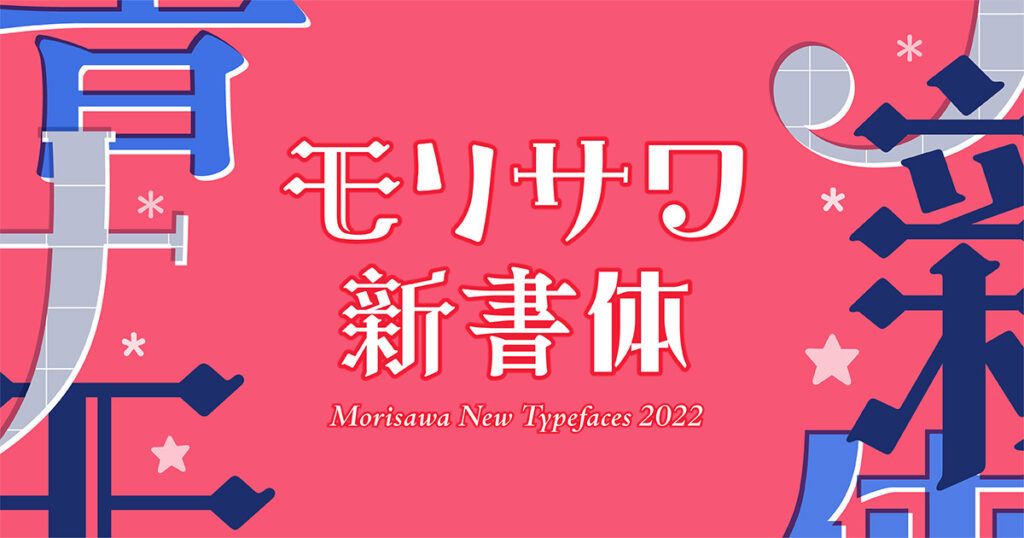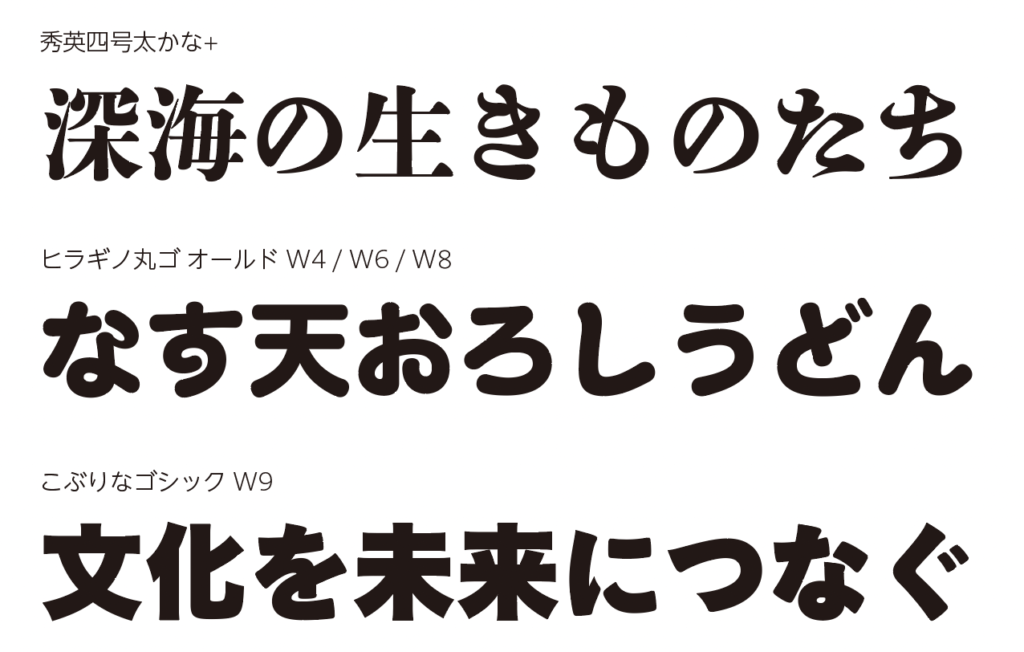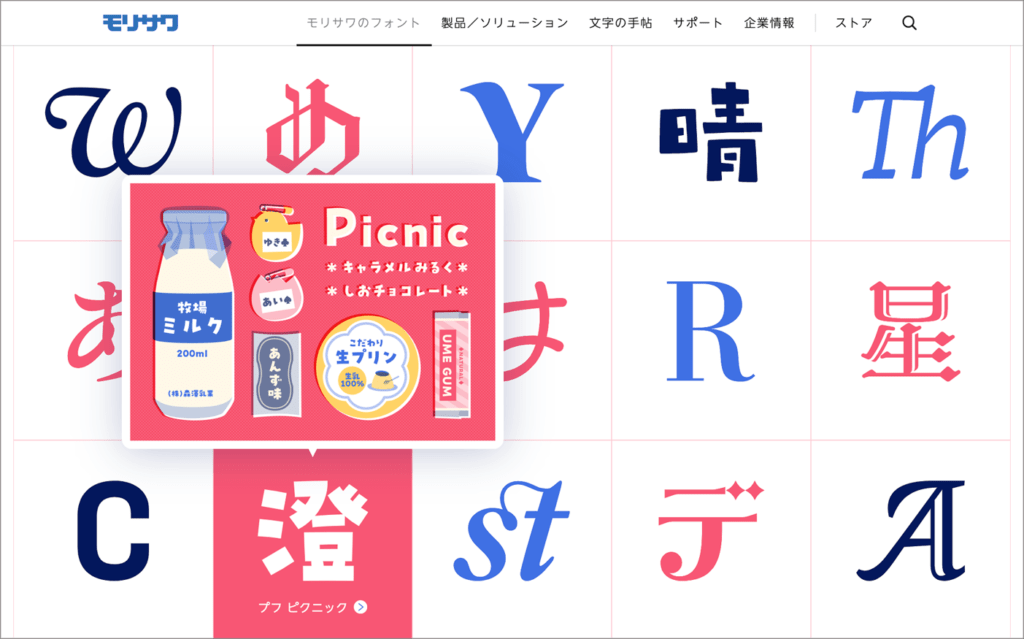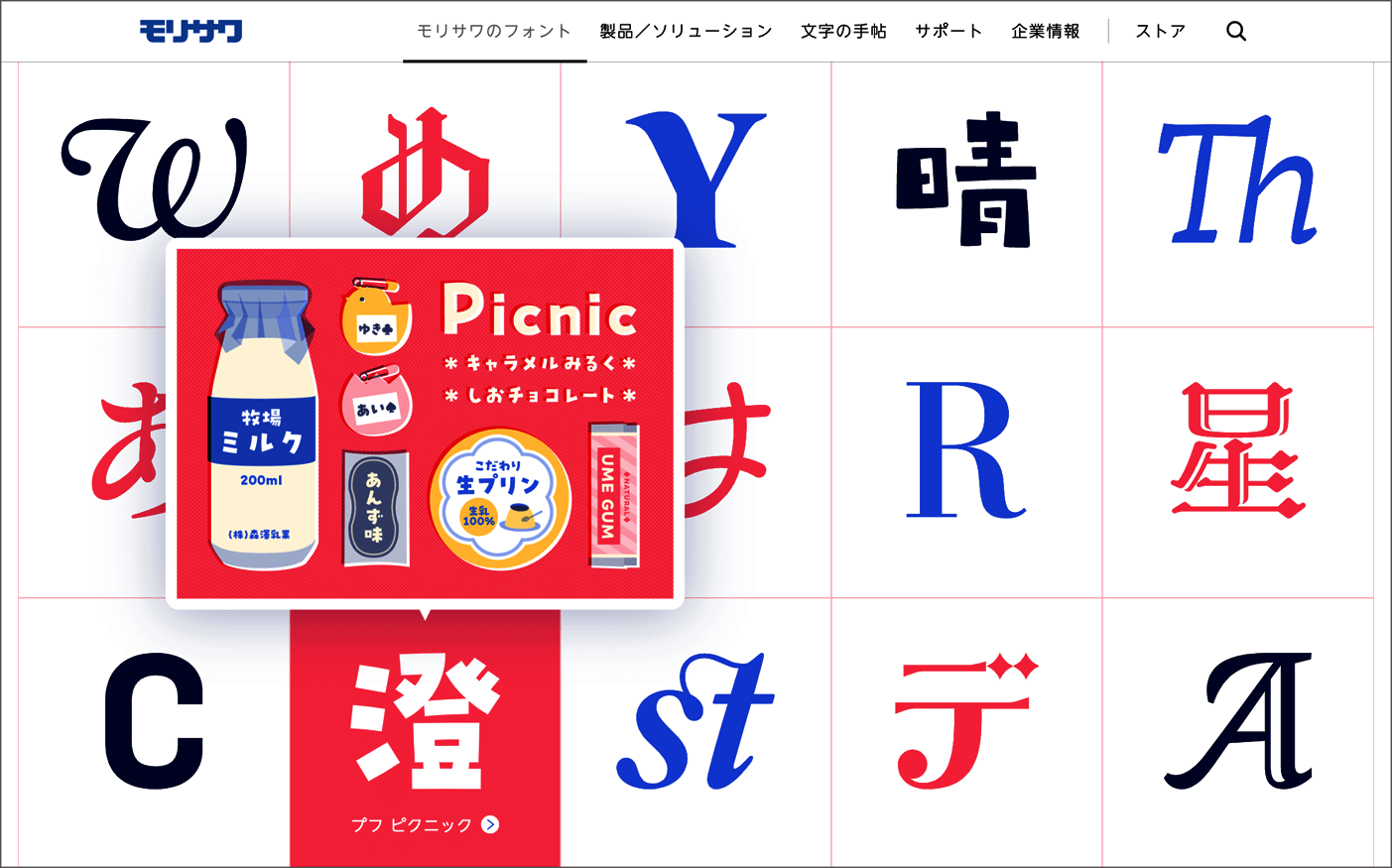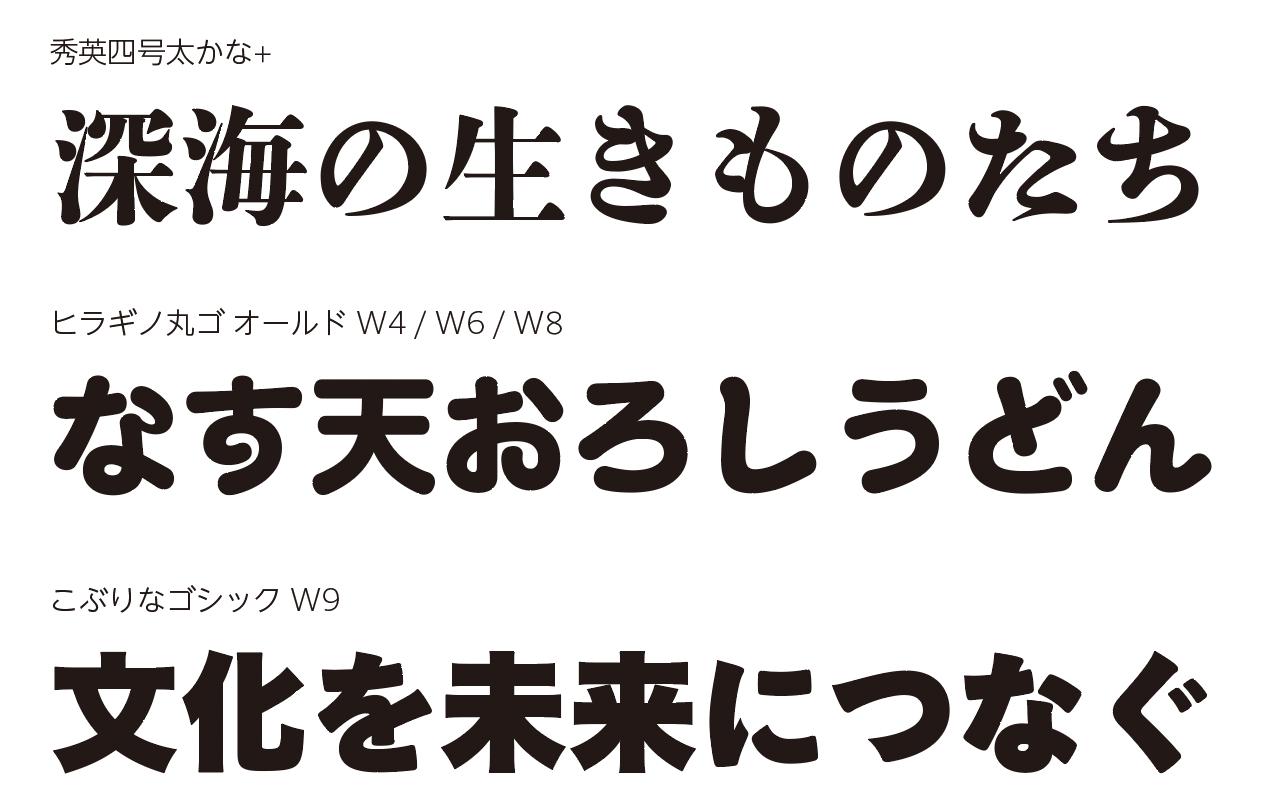
モリサワ 2022年新書体を紹介する特設ページを公開!新書体の提供は10月26日11時からスタート
株式会社モリサワは、10月26日11時より、Morisawa FontsおよびMORISAWA PASSPORT アップグレード2022年10月版として、2022年新書体の提供を開始する。
今回のアップグレードは、 合計77ファミリー500書体以上に及ぶ、 過去最大の書体数が登場する。
和文書体では『インパクト』『ゆるポップ』『ロマン』『オールド』の4つのジャンルで個性的なデザイン書体などを強化するほか、 欧文書体も『オーガニック&ディスプレイ』『クラシカル&スタンダード』『Roleスーパーファミリー』『Clarimo UDシリーズ』の4ジャンルを一挙にリリースする豪華な内容となっている。
また、 「秀英四号太かな」を「秀英初号明朝」の漢字と合わせて総合書体化した「秀英四号太かな+」や、 ユニークでどこか懐かしい書体「ヒラギノ丸ゴ オールド」も登場。 さらに今回の新書体提供にあわせて、 「リュウミン」 「ゴシックMB101」 「すずむし」をはじめとした人気書体のAP版や、 「G2サンセリフ」の文字セット追加、 定番書体「こぶりなゴシック」のウエイトも追加されている。
より自由で豊かな表現が実現する新書体の詳細については、9月27日に公開した特設ページで紹介している。
それぞれの書体の特徴や組見本を多数掲載しており、 使用イメージを提案している。